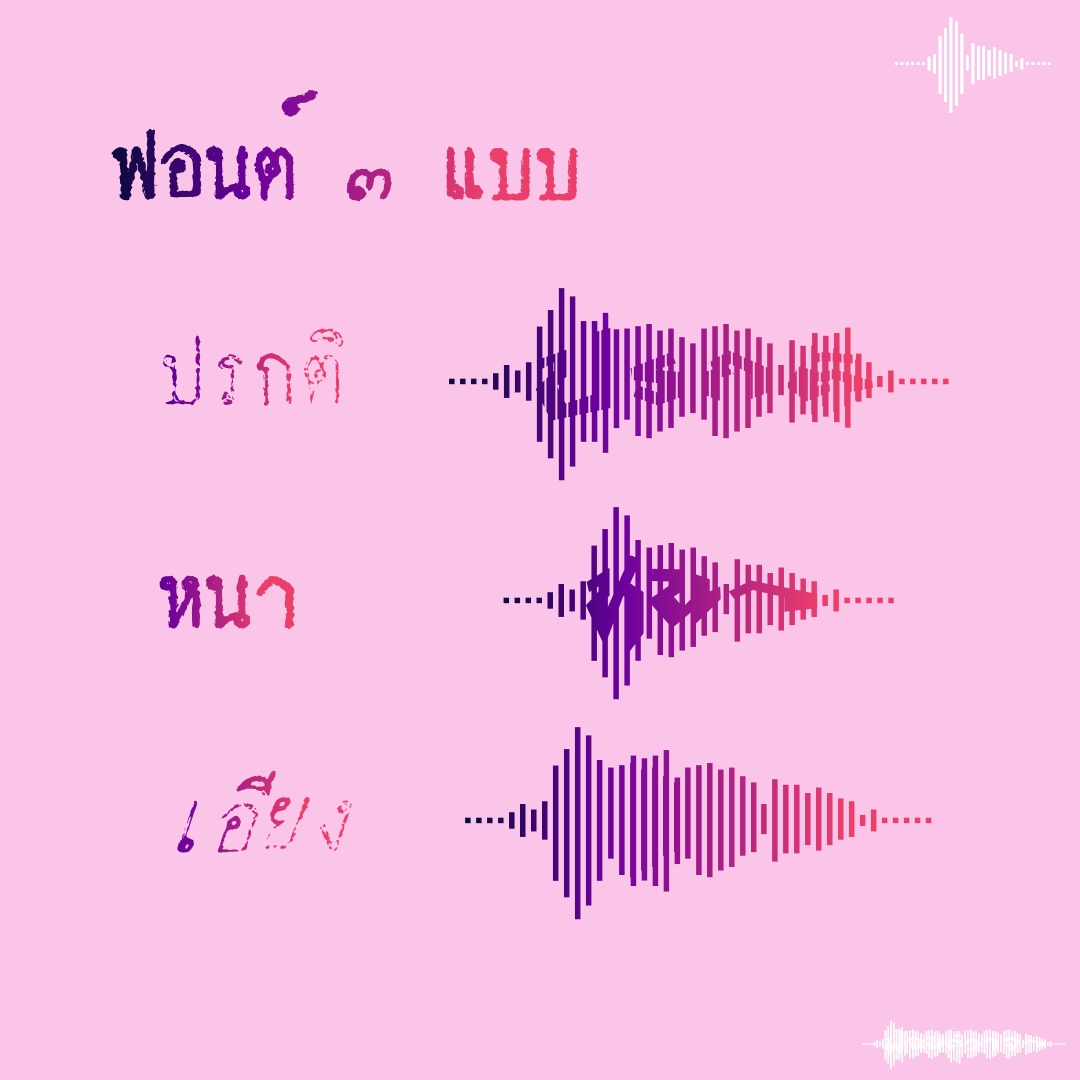
ฟอนต์ วาจา
ฟอนต์วาจา อักษรบนรูปคลื่นเสียง อักษรไทยพิมพ์ได้ปรกติ เว้นวรรคแยกคำหรือประโยค อักษรละตินใส่ไว้ในปีกกา { } ..อ่านไม่ออก ใช้ตัวหนา ไม่อยากอ่าน ใช้ตัวเอียง
ชื่อฟอนต์ : วาจา
ฟอนต์วาจา อักษรบนรูปคลื่นเสียง อักษรไทยพิมพ์ได้ปรกติ เว้นวรรคแยกคำหรือประโยค อักษรละตินใส่ไว้ในปีกกา { } ..อ่านไม่ออก ใช้ตัวหนา ไม่อยากอ่าน ใช้ตัวเอียง
BTS
เอาจริงไม่ยาก แต่ถึก..
1. ใช้ template ฟอนต์ ที่อักษรตัวแรก และตัวสุดท้ายไม่เหมือนเพื่อน (และอักษรตัวเดียวก็อยู่ได้)  ของที่เคยทำไปแล้ว
2. แต่แน่นอน ถ้าเส้นยุบยับขนาดนี้ ขนาด file ใหญ่บึ้ม และถ้าพลาด แก้ไขไม่ได้แน่
3. ปรับ template เพิ่มชุดตัวอักษร แยกอักษร กับเส้นคลื่นเสียง แล้วค่อย merge รวมกัน
หมายเหตุ และดีที่เลือกวิธีนี้ เพราะทำใหม่หลาย version มาก กว่าจะได้ความลงตัว  ..และอานิสงค์คือ ทำให้ตัวหนา ตัวเอียง ง่ายมาก
เอ๊ะ หมายถึงแต่ละ glyph จะมีแค่ตัวอักษร แล้วเขียนโค้ดให้เอาคลื่นมารวมเองเหรอครับ :18:
หรือถ้าไม่ได้ใช้วิธีนี้ ถ้าทำอย่างที่ว่าได้ (คือพิมพ์ตัวใดๆ ก็ตาม ให้ดึงเครื่องประดับมาใส่ไว้เสมอ)
น่าจะสนุกและต่อยอดได้อีกเยอะมากๆ เลยนะครับนี่
จ๊าก!! :18: ไม่ใช่ขนาดนั้น :48:  คือ glyph ในรูปที่ 2 เกิดเป็น link ที่เกิดจาก glyph ในรูปที่ 3 แค่นั้นจ้า..  แต่ว่ามันก็ช่วยได้เยอะ เช่น ตอนแรกที่ทำ glyph เส้นคลื่นมันถี่ไป เราก็แค่แก้ glyph ในรูปที่ 3 แค่ 10 กว่าตัว ไม่ต้องตามแก้ 200 กว่าตัวครับ
หรือถ้า design ฟอนต์ใหม่ .. แค่เอามาวางแทน ตัวแหน่งเดิม ก็จะได้ฟอนต์ที่อยู่ในคลื่นเสียงเลยครับ
(ในฟอนต์ ทิ้ง glyph ที่ทำหน้าที่ ตัดตัวอักษรให้เป็นแท่งๆ ไว้ให้ด้วยไม่ได้ลบออก .. แค่ต้องทำกรรมวิธีอีกหน่อยนึง)
ถ้าทำได้จริง ให้นึกเร็วๆ ก็คงเหมือน ฟอนต์ที่เป็นกรอบแบบแป้นคีย์บอร์ด, ฟอนต์ที่ใส่หางแมว :30: หรือฟอนต์ขีดฆ่า
โดย glyph ก็จะสะอาด จะมีแค่ glyph พิเศษที่มีหน้าที่เติมแต่งไว้ท้ายๆ แค่นั้น ไฟล์ฟอนต์ก็จะเล็กด้วย อะไรแบบนี้ครับ
และในโปรแกรมกราฟิกสามารถจิ้มเลือกตัวอักษรเพียวๆ แบบไม่มีเครื่องประดับได้เลย
ประมาณนี้ไหมครับ https://www.typotheque.com/fonts/history#tester --> จิ้มที่ตัวอักษรแล้ว ปรับแต่ง style ตามที่ต้องการ
การใช้งานเป็น layer ..ข้อดี ทำเป็น style apply กับทุก glyph  ข้อเสีย อยากจะทำเป็นตัวๆเว้ย!!!
ผมว่า ปัญหาอยู่ที่การออกแบบ การใช้งานฟอนต์ครับ .. เนื่องจาก มาตรฐาน ในการเปลี่ยนรูปร่าง glyph ตอนนี้(alt,ss01,02,..)มันยังระบุไปยัง glyph ที่เตรียมไว้ล่วงหน้า
แม้แต่ฟอนต์สีที่รองรับการ glyph เปลี่ยนสีผิว เปลี่ยนทรงผม ก็ยังต้องเตรียม glyph ไว้ล่วงหน้า แต่กำหนด script วิธีใช้ไว้ให้
ตอนนี้ยังไม่มี function ให้ทำการ ซ้อน (layer) ได้  ถ้ามีก็จะใช้งานง่ายเลย
--> ในตัวอย่างฟอนต์นี้ เขาทำ tools มาจัด layer ให้ด้วย จะได้เข้าใจง่าย (แถมแยกขาย style font ได้อีก) ไม่ต้องซื้อไปลองใน PS, AI เอง
กรณีไม่อยากรอมาตรฐานใหม่ ที่พอ apply ได้ ก็คือ variable font ที่สามารถซ่อน หางแมว, ขีดฆ่า (แต่ไม่ได้ file ขนาดเล็ก และการจะทำเป็นตัวๆน่าจะเหนื่อยอยู่)
อีกวิธี ก็เขียน script กำหนดเอง (liga) อันนี้ไม่ยาก แต่ไม่มาดถาน เช่นเคยยยย